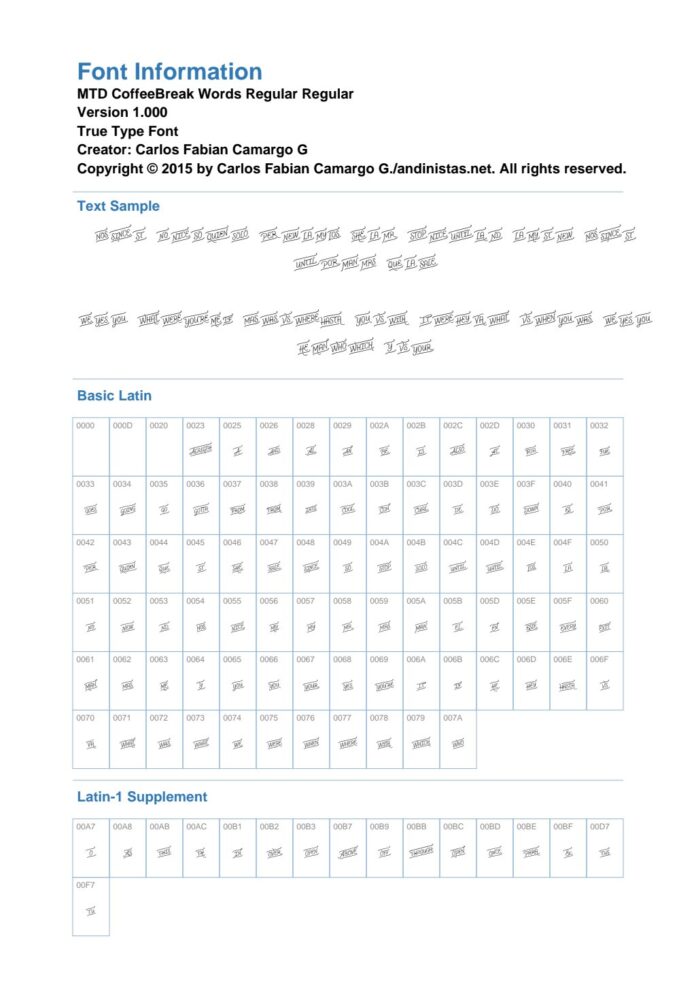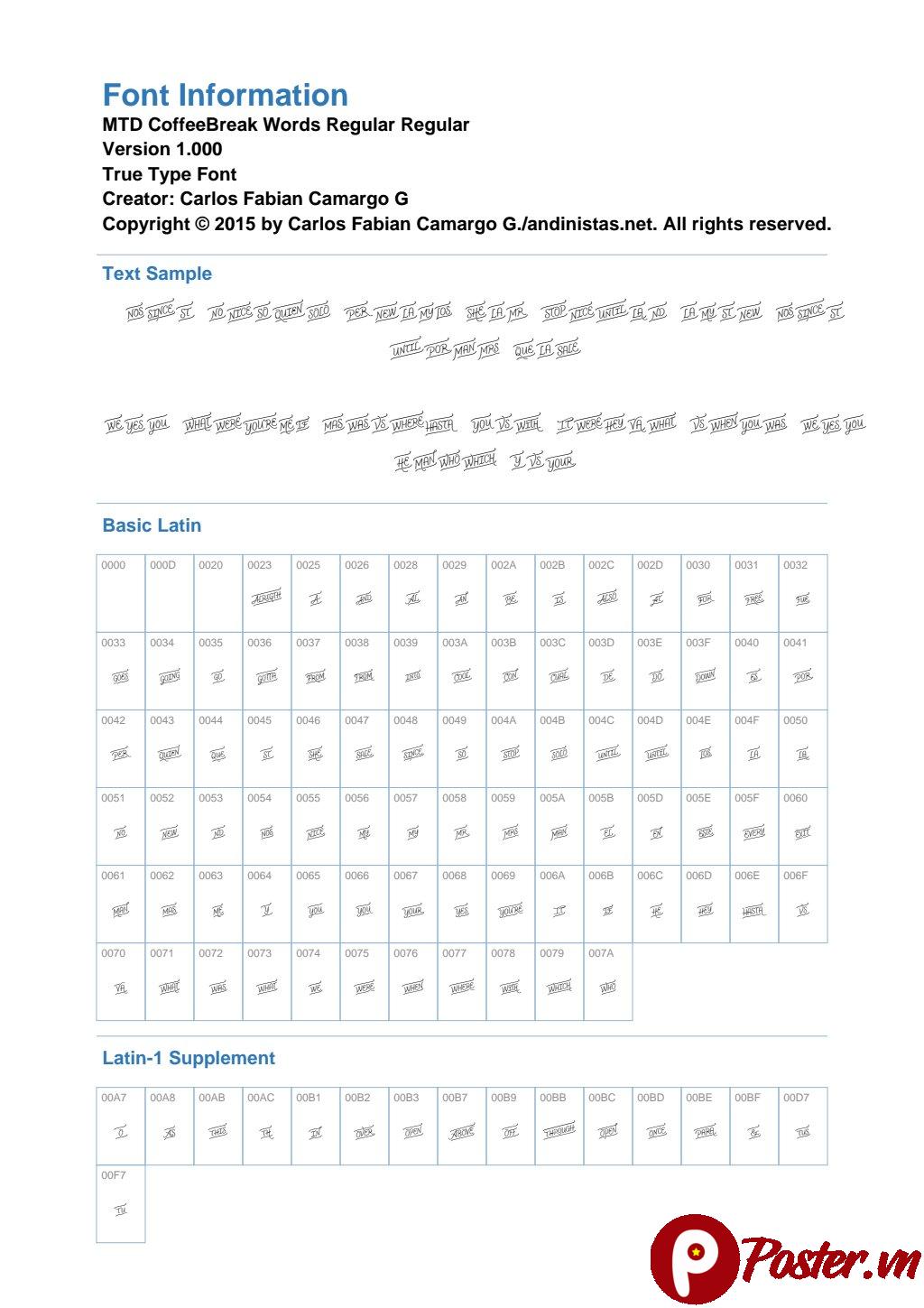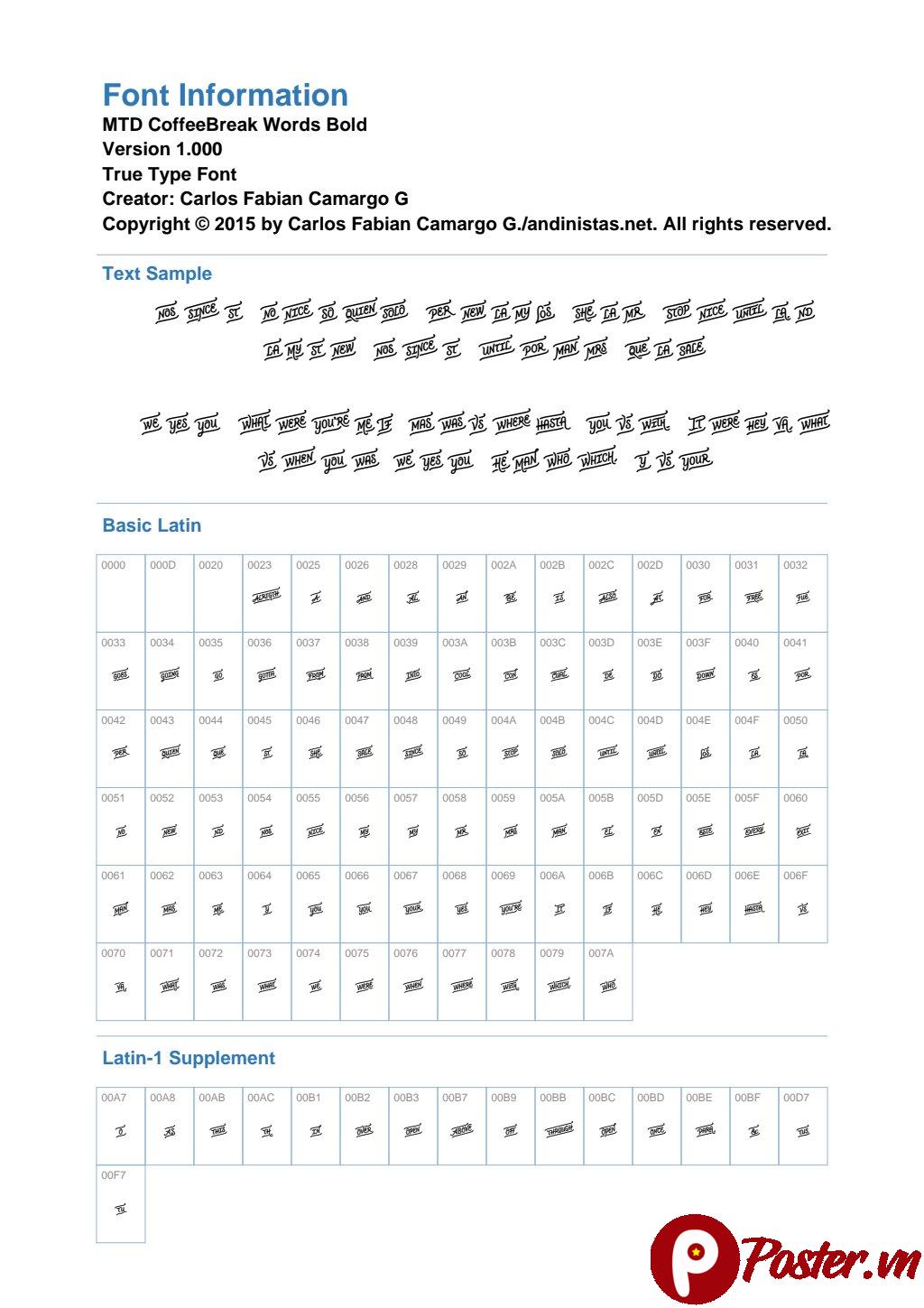
Font MTD CoffeeBreak Words – Nét Độc Đáo
Font MTD CoffeeBreak Words – Nét Độc Đáo: Khám phá MTD CoffeeBreak Words Regular – phông chữ viết tay với nét chữ bay bổng, thư giãn, lý tưởng cho thiết kế cần sự sáng tạo và cá tính. Tệp tin .ttf chất lượng cao, dung lượng 290 KB, dễ dàng tích hợp vào mọi dự án đồ họa.
Giới thiệu Phông Chữ MTD CoffeeBreak Words Regular: Nét Chữ Bay Bổng Cho Mọi Thiết Kế
Trong thế giới thiết kế đồ họa, việc lựa chọn một phông chữ phù hợp không chỉ đơn thuần là chọn một kiểu chữ, mà là lựa chọn một “giọng điệu” truyền tải thông điệp và cảm xúc. MTD CoffeeBreak Words Regular chính là một trong những viên ngọc quý mang đến “giọng điệu” độc đáo, đậm chất nghệ thuật và thư giãn. Đúng như tên gọi của nó, phông chữ này gợi lên hình ảnh một buổi “coffee break” nhẹ nhàng, nơi những ý tưởng mới mẻ được hình thành và dòng chảy sáng tạo không ngừng tuôn trào.
Được thiết kế với phong cách viết tay ngẫu hứng, MTD CoffeeBreak Words Regular mang đến sự mềm mại, bay bổng với những nét mảnh, không đều nhưng đầy tinh tế. Mỗi ký tự dường như được vẽ bằng tay một cách tự do, tạo cảm giác gần gũi, thân thiện và đầy tính cá nhân. Đây không chỉ là một phông chữ; đó là một tuyên ngôn về sự tự do trong thiết kế, một lời mời gọi để bạn thể hiện cá tính riêng biệt trong từng dự án.
Phông chữ này là lựa chọn hoàn hảo cho những ai tìm kiếm sự phá cách, muốn thoát khỏi những khuôn mẫu cứng nhắc để tạo nên những tác phẩm đồ họa có chiều sâu và cảm xúc. Dù bạn đang thiết kế logo cho một quán cà phê ấm cúng, tạo ra thiệp mời sự kiện độc đáo, hay đơn giản là muốn làm mới giao diện bài đăng trên mạng xã hội, MTD CoffeeBreak Words Regular sẽ là “trợ thủ” đắc lực, thổi hồn vào từng dòng chữ, biến chúng thành tác phẩm nghệ thuật thu hút mọi ánh nhìn.
Phông chữ này được tạo bởi **Carlos Fabian Camargo G** và phát hành dưới bản quyền © 2015 bởi Carlos Fabian Camargo G./andinistas.net. Thông tin về người tạo rõ ràng cho thấy đây là một sản phẩm được phát triển chuyên nghiệp, mang giá trị nghệ thuật và kỹ thuật. Tài liệu thông tin về phông chữ thường được trình bày trên nền trắng sạch sẽ, với các tiêu đề chính như “Font Information”, “Text Sample”, “Basic Latin” và “Latin-1 Supplement” được làm nổi bật bằng màu xanh dương đậm, giúp người dùng dễ dàng nắm bắt các chi tiết quan trọng về bộ ký tự và tính năng của phông chữ.
Đặc Điểm Nổi Bật Của MTD CoffeeBreak Words Regular: Sự Kết Hợp Giữa Nghệ Thuật và Chức Năng
MTD CoffeeBreak Words Regular không chỉ là một phông chữ đẹp mắt mà còn sở hữu nhiều đặc điểm kỹ thuật và thẩm mỹ nổi bật, biến nó thành một công cụ không thể thiếu cho các nhà thiết kế:
Tính Thẩm Mỹ Độc Đáo
• Phong Cách Viết Tay Ngẫu Hứng: Nét chữ mảnh, lượn sóng, không đều tạo nên vẻ đẹp tự nhiên, chân thực như được viết bằng bút chì hoặc bút mực. Sự ngẫu hứng này mang lại cảm giác thân thiện, không gò bó.
• Cảm Giác Nhẹ Nhàng, Bay Bổng: Các nét cong, đôi khi chồng lên nhau, tạo hiệu ứng thị giác mềm mại, uyển chuyển. Điều này đặc biệt phù hợp để truyền tải sự thư giãn, mơ mộng hoặc sự sáng tạo không giới hạn.
• Font MTD CoffeeBreak Words phong cách viết tay nguệch ngoạc, cá tính
• Gợi Nhắc Không Khí “Coffee Break”: Tên gọi và phong cách thiết kế hòa quyện, mang đến cảm giác ấm áp, thư thái của một buổi nghỉ giải lao bên tách cà phê, khơi gợi cảm hứng sáng tạo.
• Sự Kết Hợp Giữa Cổ Điển và Hiện Đại: Mặc dù là phông chữ viết tay, nó vẫn giữ được sự rõ ràng và dễ đọc, khiến nó phù hợp với nhiều bối cảnh khác nhau, từ phong cách vintage đến hiện đại tối giản.